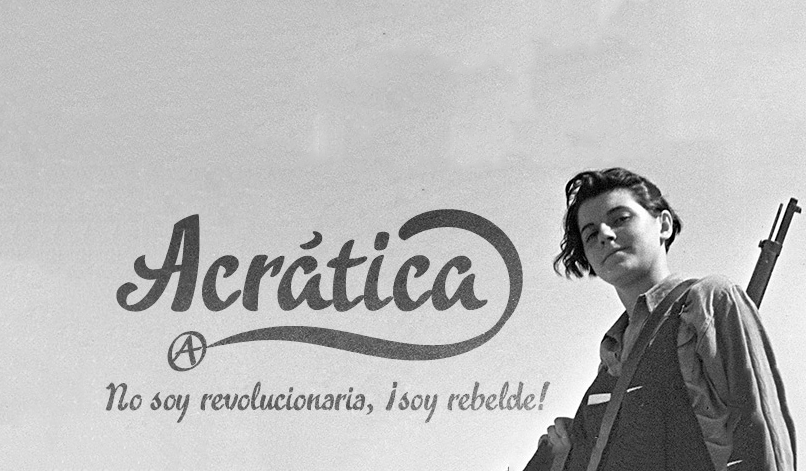
Acrática é uma fonte tipográfica escrita a mão que adota estilos serifados, repleta de setores ornamentais e contornos de terminação com design único para a decoração de frases e títulos. Este projeto foi dedicado a todos os libertários do mundo, incluindo o símbolo Bitcoin: b #. Esta fonte é livre para uso pessoal apenas. Grata pela sua descarga.